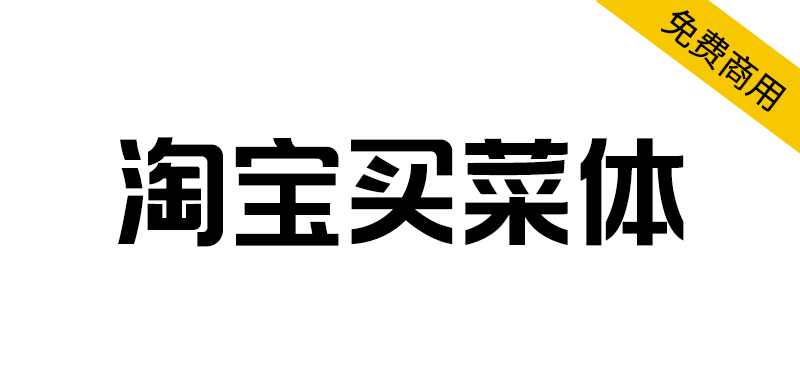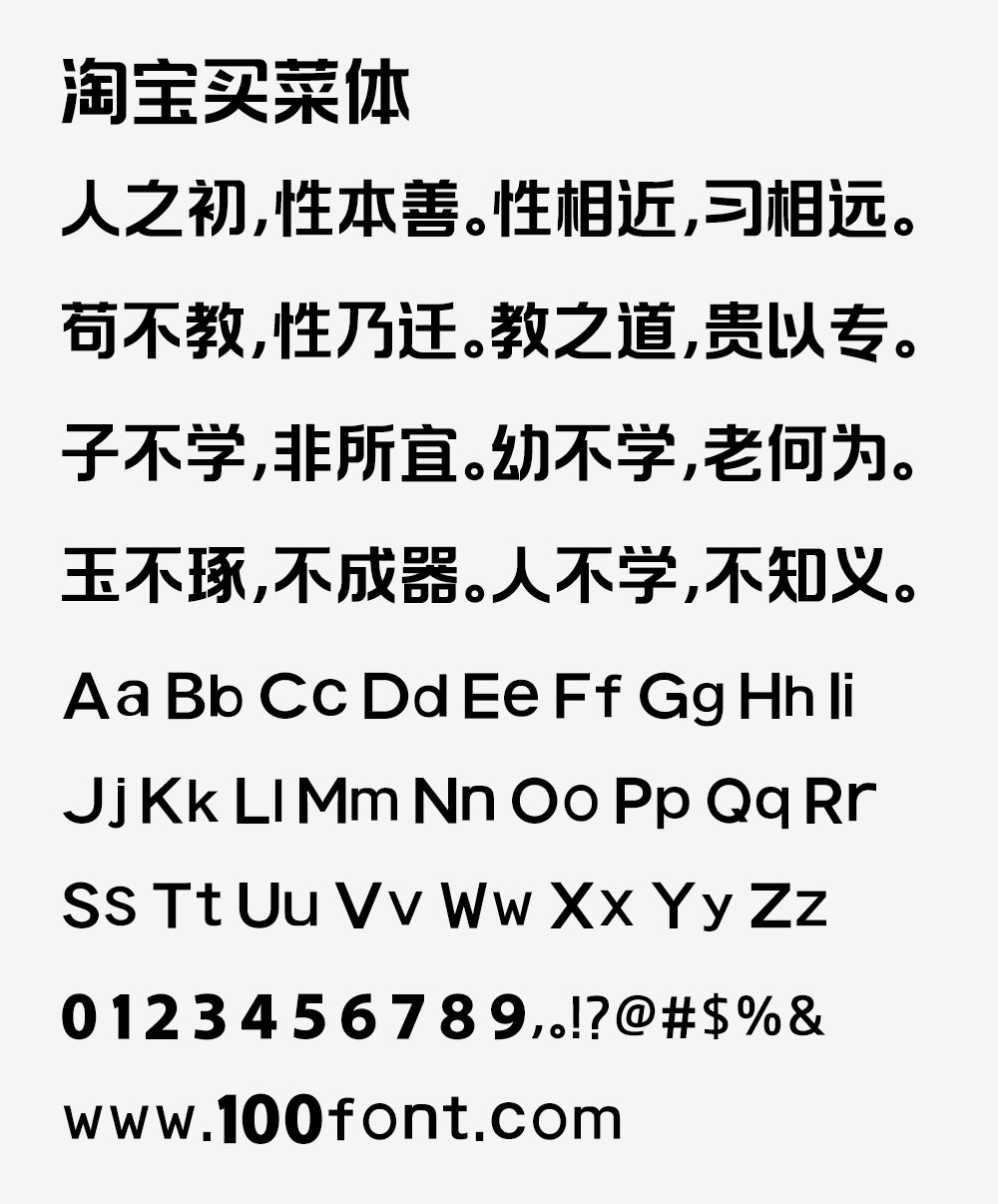
淘宝买菜体又叫淘宝买菜营销体,是淘宝买菜携手通义锦书,倾力打造了一款独具匠心的AI个性化字体。这款智能AI字体不仅拥有丰富的中文字符库,覆盖GB2312标准,包含超过6974个汉字,更通过智能AI技术,赋予字体独特的质感和生命力。我们精心挑选了7套质感图片,现已广泛应用于淘宝买菜的各个场景,显著提升了运营和设计团队的工作效率,达到了20%的效率提升。